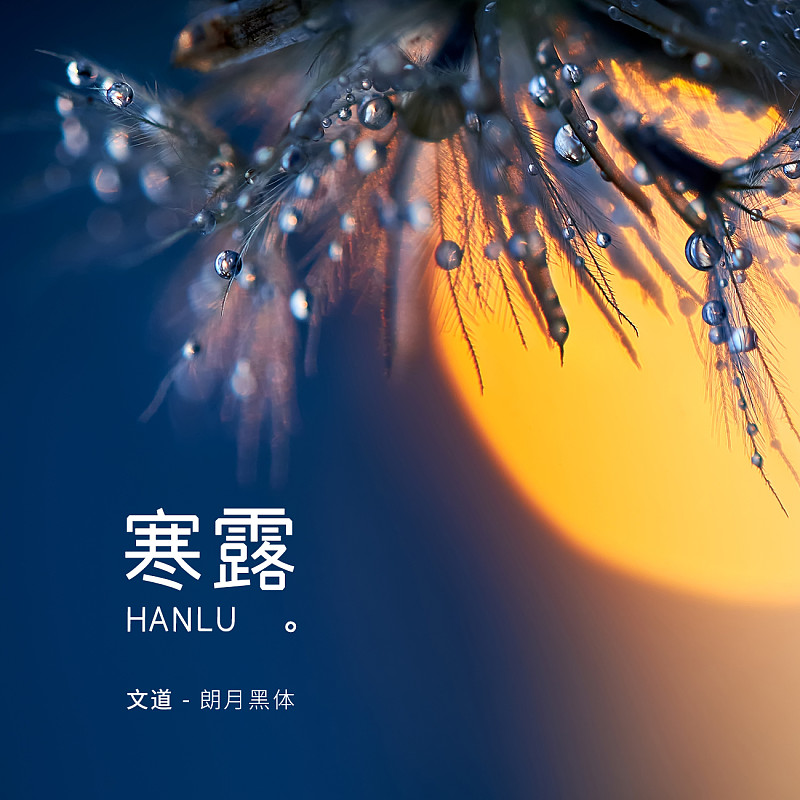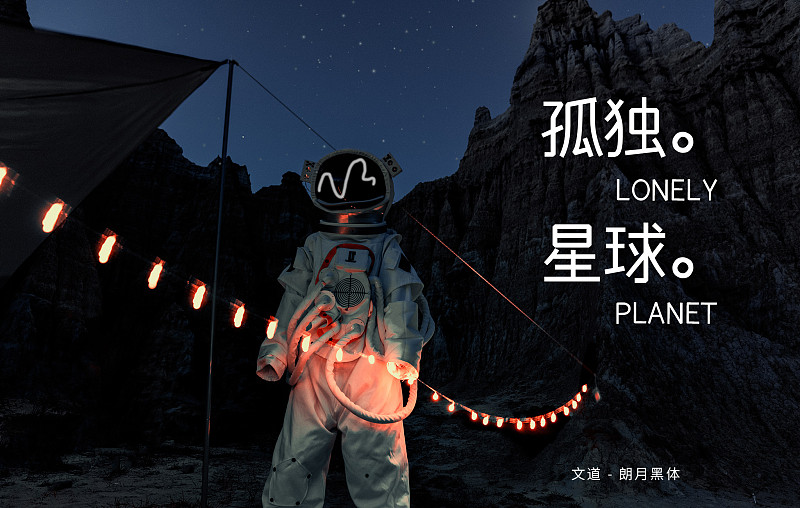
文道朗月黑
字形結構源于傳統黑體,為單個設計師獨立完成,字面大小及筆畫粗細得到整體的協調。 設計師此款設計筆畫進行鏡像對稱處理,將所有鉤筆和折筆部分加入輕微切角。 文道朗月黑的字形風格清朗有力,字形欣長又中和內斂,追求字體整體和諧,除了滿足傳統印刷媒介的各類標題,還適用于屏幕顯示、廣告標語和包裝設計